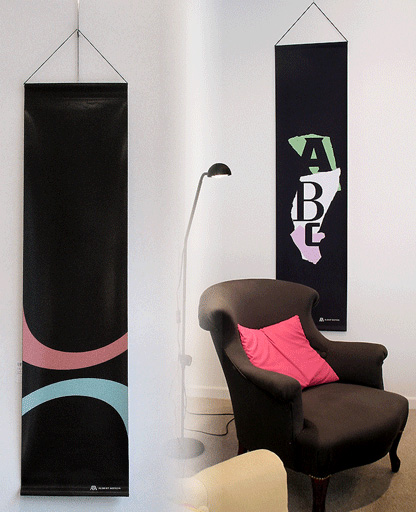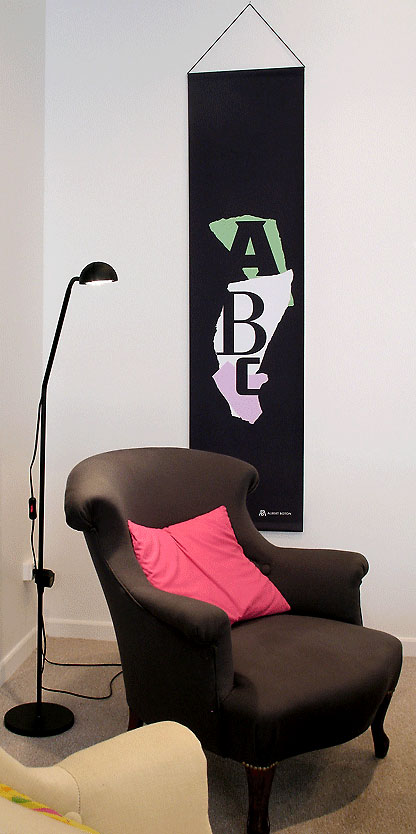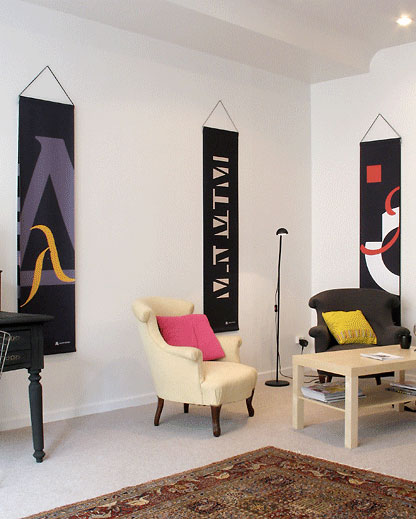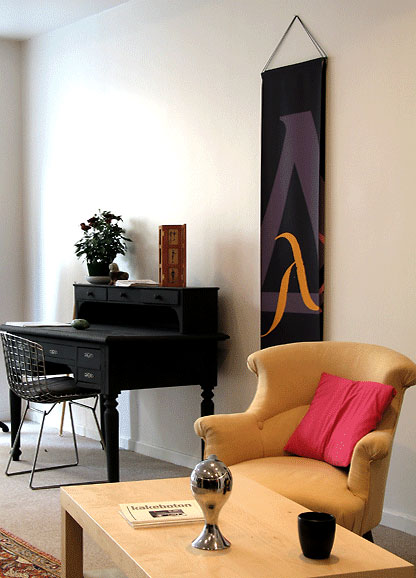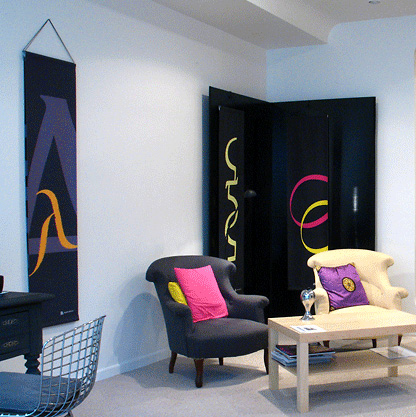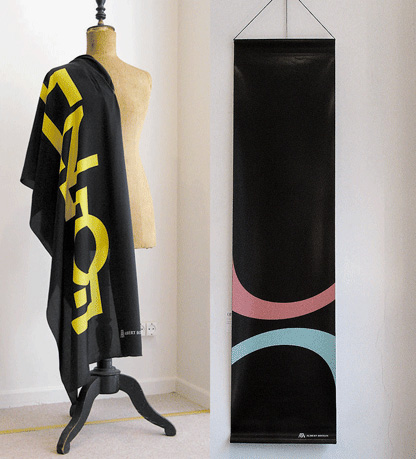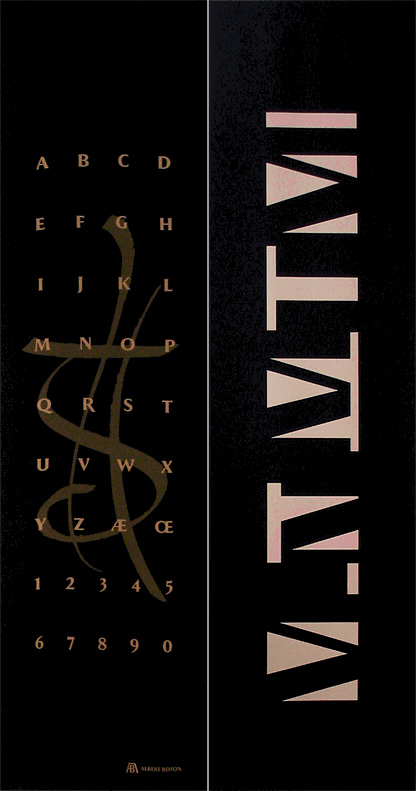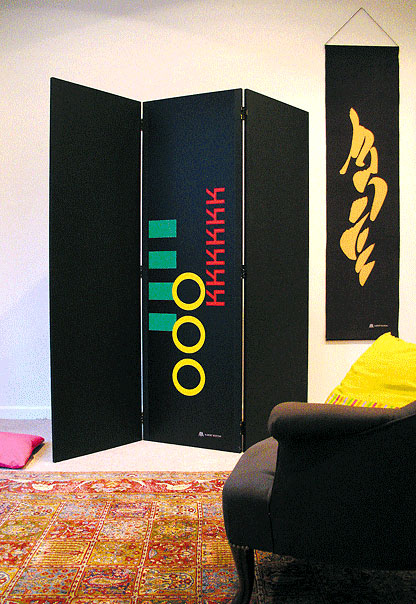
Albert Boton, classique parmi les classiques, après avoir passé sa vie à construire des formes graphiques d’un classicisme avéré, devient moderne en déstructurant les formes typographiques pour le bonheur de nos yeux. Pour le mai du livre d’Art et organisé par la Bibliothèque de la Ville, à l’Espace Landowski du 9 mai au 15 juin 2007, le créateur de caractères Albert Boton s’expose à Boulogne Billancourt.